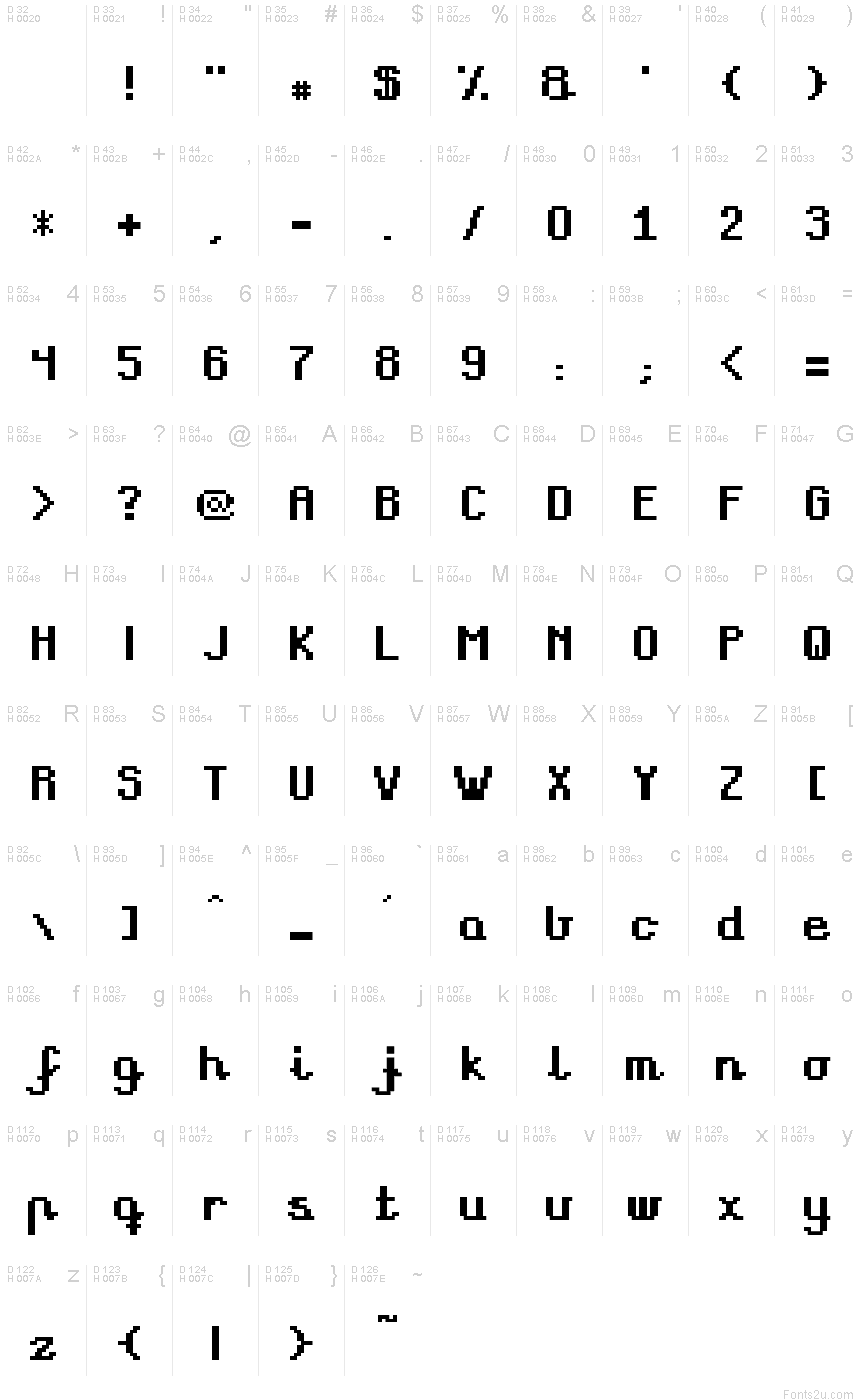
Podgląd czcionki Teachers Pet Bold
Teachers Pet Bold od Orgdot to darmowy font bitmapowy z masywnymi, pikselowymi literami i przyjaznym, niskorozdzielczym charakterem. Kwadratowe narożniki, schodkowe krzywe i grube monolinowe bloki nadają tekstowi domowy klimat ery wczesnych monitorów – coś pomiędzy szkolnym oprogramowaniem a dawną grafiką komputerową.
Użyj tego darmowego kroju pisma do nagłówków plakatów, okładek zinów, menu gier, systemów etykiet i krótkich banerów internetowych, gdzie surowa pikselowa faktura buduje nastrój. Sprawdza się również świetnie w czołówkach i wyróżnionych cytatach, ponieważ litery sprawiają wrażenie solidnych i nieformalnych, a nie wygładzonych.